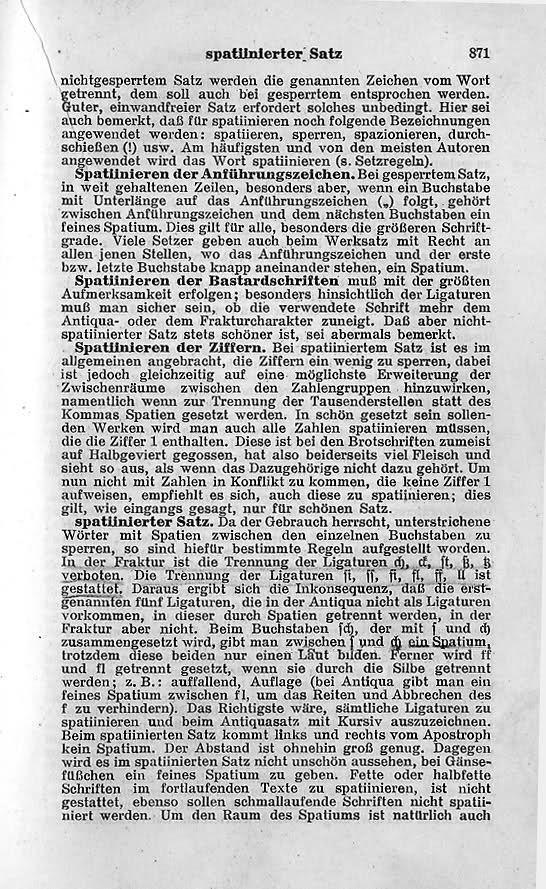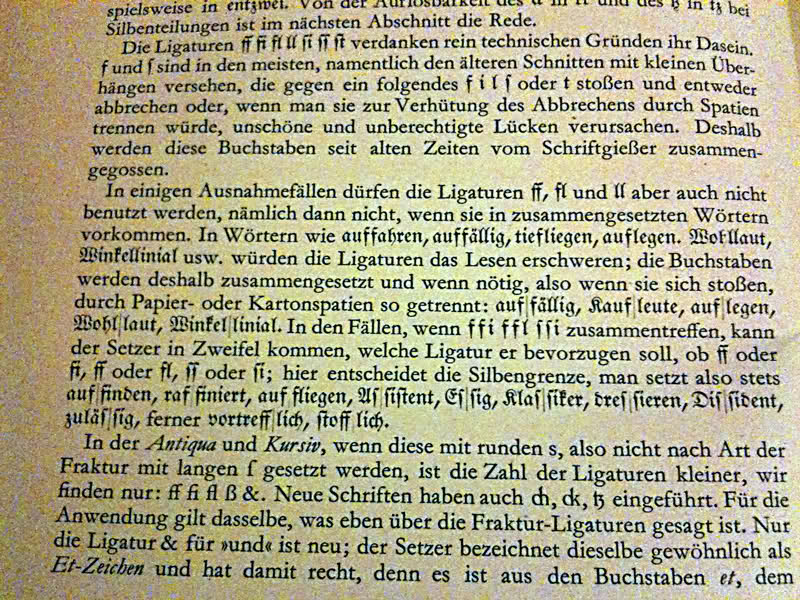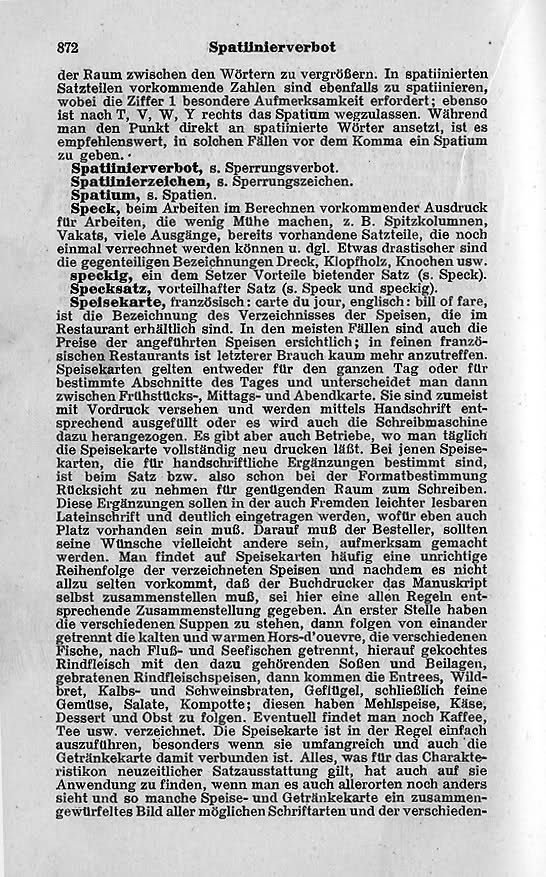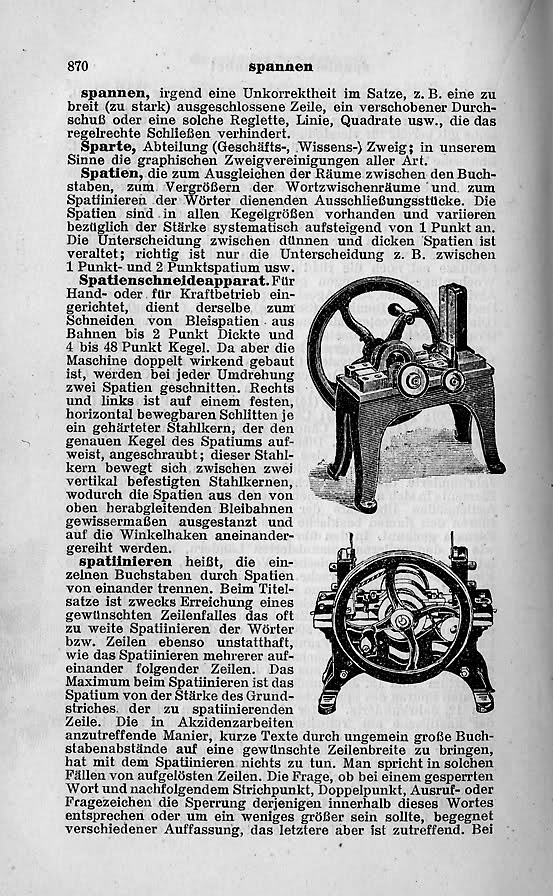
Zwangsverbünde im gesperrten Fraktursatz: Das ſt
Die Passage zum Thema „Sperren“ aus dem satztechnischen Taschen-Lexikon, Richard L. Niel, zweite Auflage, Wien 1925.
Diese Information ist falsch, denn die Ligatur ‹?t› gehört doch auch zu den obligatorischen Ligaturen!
So einfach kannst Du es Dir nicht machen. Das vollständige theoretisch-praktische Handbuch der Typographie wurde 1870 herausgegeben, und was Marahrens darin schreibt, ist sicher nicht falsch.
Du gibst ja selbst zu, daß ?t nicht einheitlich gehandhabt wird (wurde). Daran ist sicher nicht der Duden „schuld“. Ich vermute, daß ?t ursprünglich (wie Marahrens es beschreibt) nicht zu den Zwangsverbünden gehört hat, später aber häufig so behandelt worden ist, möglicherweise (auch) wegen der Regel, daß ?t nicht getrennt werden darf.
Letztendlich wird/wurde ?t später also wohl teilweise als Zwangsverbund behandelt, teilweise nicht, und teilweise „halb“ (ungesperrte Einzelbuchstaben im Sperrsatz).
Letztendlich wird/wurde ?t später also wohl teilweise als Zwangsverbund behandelt, teilweise nicht,
Nur sehr sehr selten nicht. Bislang habe ich das nur in einigen Büchern von Cotta aus dem ersten Jahrzent des 19. Jahrhunderts gesehen. Bei einer Stichprobe von Cotta-Büchern aus der Zeit zwischen 1830 und 1850 habe ich hingegen bei einer Sichtung der ersten 30 Resultate kein einziges Werk mehr gefunden, wo das ?t nicht als obligatorische Ligatur gesetzt gewesen wäre. Das scheint mir ein weiteres Indiz dafür zu sein, das es sich bei den Werken ohne obligatorische ?t-Ligatur um Ausreisser aus einer frühen Zeit handelt, als die typographischen Regeln noch nicht so gefestigt waren.
und teilweise „halb“ (ungesperrte Einzelbuchstaben im Sperrsatz).
Das ist die Behauptung aus dem Leipziger Duden von 1968, die ich noch kein einziges Mal habe beobachten können.
nur als Randbemerkung:
In Martin Luthers Sendbrief vom Dolmetschen (textgetreue Nachdrucke von Niemeyer, Halle 1951) verwenden beide , der Nürnberger und der Wittenberger Drucker, die beiden Buchstaben s und t als Ligatur - und das im Jahr des Herrn 1530.
was aber die Sperrung angeht, hat Pachulke gesagt -
ſt wurde nie einheitlich gehandhabt. In Marahrens Handbuch der Typographie (1870) gehört es ausdrücklich nicht zu den Zwangsverbünden. Diese sind dort: ch, ck, ß und tz.
Ich bin der Sache jetzt endlich auf den Grund gegangen. Es verhält sich genau so, wie ich es schon von Anfang an behauptet habe: Das ‹ſt› gehört ganz eindeutig zu den nicht-sperrbaren Ligaturen.
Joshua hat im Beitrag Re: Neuster Schrei(?): Ortsteilschilder Marahrens (1870, S. 33) zitiert:
Es giebt in der Fraktur, soweit dieselbe zur deutschen Sprache benutzt wird, zweierlei zusammengegossene Buchstaben, nämlich [einmal, erg. v. mach] solche, von denen die Sprache selbst, die Orthographie, eine Verbindung zweier erfordert, als ch, ck, ß, tz, und dann solche, welche im Interesse der typographischen Schönheit und Nützlichkeit verbunden sind: ſſ, ſi, ll, fl, fi und ſt.
An dieser von Joshua zitierten Stelle geht es überhaupt gar nicht um die Sperrbarkeit, sondern um eine Differenzierung zwischen zwei Arten von Ligaturen, orthographisch erforderliche und typographisch nützliche.
Dort hingegen, wo es um das Spatiinieren (Sperrsatz) geht, sagt Marahrens klipp und klar, dass das ‹ſt› zu den nicht-sperrbaren Ligaturen gehöre: «Bei spatiiniertem Satz haben wir nur die Ligaturen tz, ſz, ck, ch und ſt; die übrigen – also ſſ, ſi, ll, fi, ff, fl – werden zusammengesetzt und als zwei Buchstaben betrachtet, folglich auch durch Spatien getrennt» (a.a.O., S. 82).
Ferner wird bei einem kurzen Blick in das Buch sofort klar, dass im Sperrsatz das ‹ſt› offensichtlich nicht gesperrt wird.
Literatur: Marahrens, August (1870): Vollständiges theoretisch-praktisches Handbuch der Typographie nach ihrem heutigen Standpunkt. Erster Band: Das Setzen in seinen verschiedenen Branchen. Leipzig: Leipziger Vereinsbuchdruckerei. URL: http://openlibrary.org/ia/vollstndigesthe00maragoog (abgerufen 2010-12-05).
Fazit: Die einzige theoretische Schrift, die das ‹ſt› für sperrbar erklärt, ist der Duden in seinen neusten Ausgaben. Die einzigen bis jetzt hier angeführten Drucke, wo das ‹ſt› gesperrt worden wäre, stammen noch aus dem frühen 19. Jahrhundert. Übrigens finden sich auch Beispiele, wo ‹st› an Stelle von ‹ſt› gesetzt worden ist – und das nimmt ja auch niemand als Anlass für die Behauptung, man habe das ‹ſ› nie einheitlich gehandhabt.
Hoppla. Du hast recht. Wie konnte ich das übersehen?! :-o
Es ist ja aber schon eine seltsame Sache: Nicht sperrbar sind also die sprachlich nötigen Verbünde und dazu noch das ſt.
Diese Sonderstellung des ſt hat sicher mit der Sonderregel zu tun, daß ſt auch nicht getrennt werden darf. Bis heute ist ja ungeklärt, worauf diese Regel überhaupt zurückzuführen ist.
Meine Vermutung ist, dass die vormalige Untrennbarkeit von ‹st› denselben Grund hatte wie die Unspatiinierbarkeit der Ligaturen ‹ch ck ſt ſz tz›: Die Gewohnheit der alten Bleilettern.
Ergo würde ich im Umkehrschluß im gesperrten Satz auf Ligaturen verzichten, da die technische Notwendigkeit dafür fehlt.
Das sollte man ja eigentich auch meinen – und gerade darum ist es ja auch so erstaunlich und ungewöhnlich, dass im gesperrten Fraktursatz die Ligaturen ch, ck, ſt, tz als ungesperrte Ligaturen beibehalten werden. Vermutlich dürfte das auch in dem von dir genannten Handbuch für Schriftsetzer stehen, nur halt in dem Abschnitt, wo es um den gesperrten bzw. spatiinierten Satz geht.